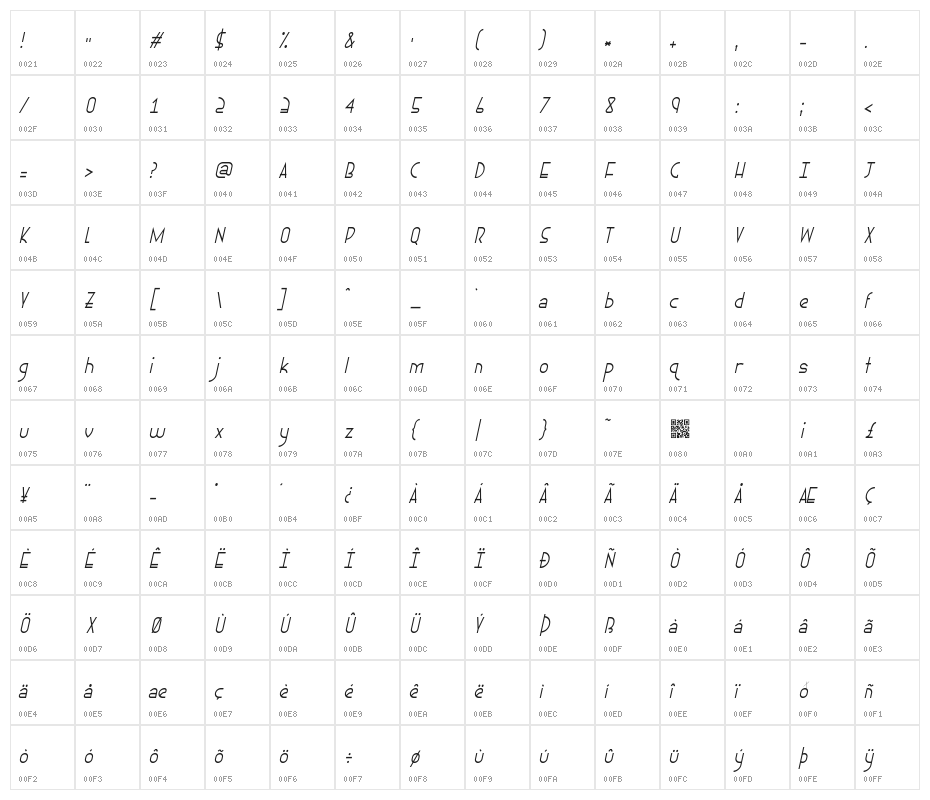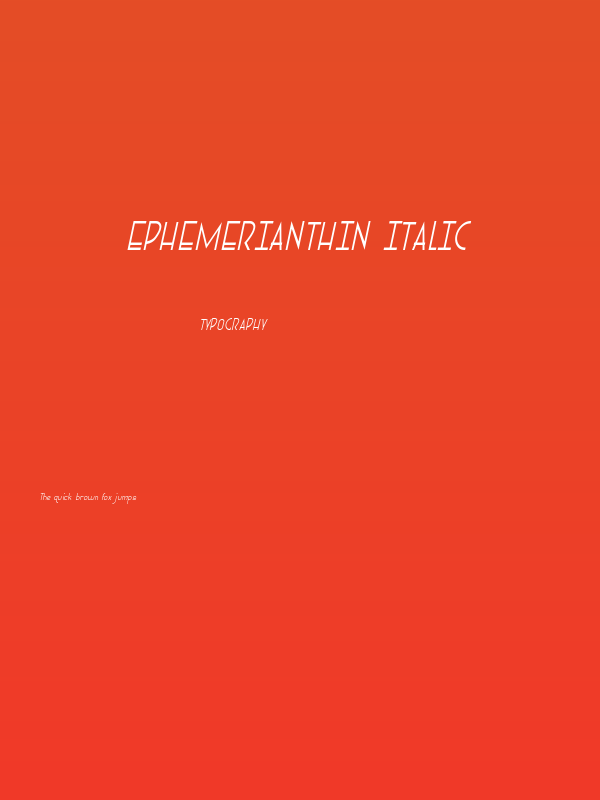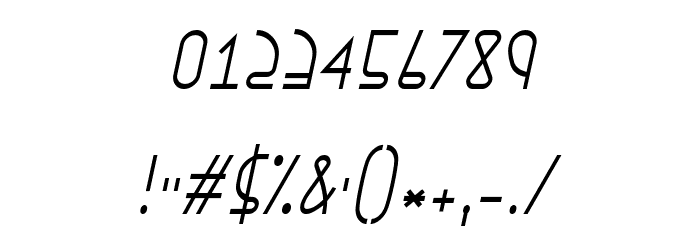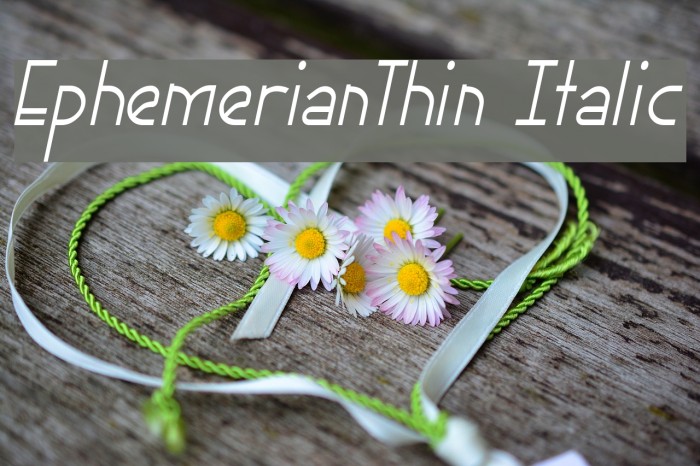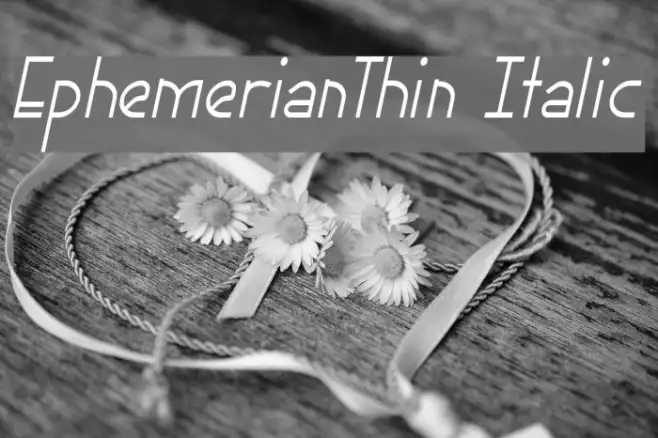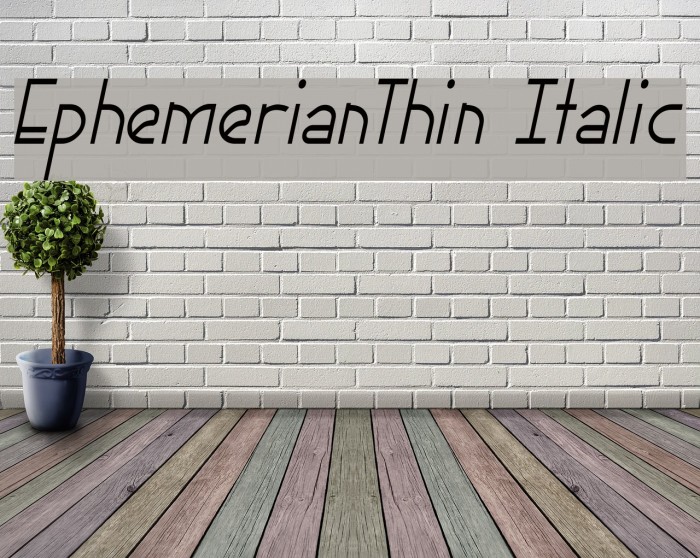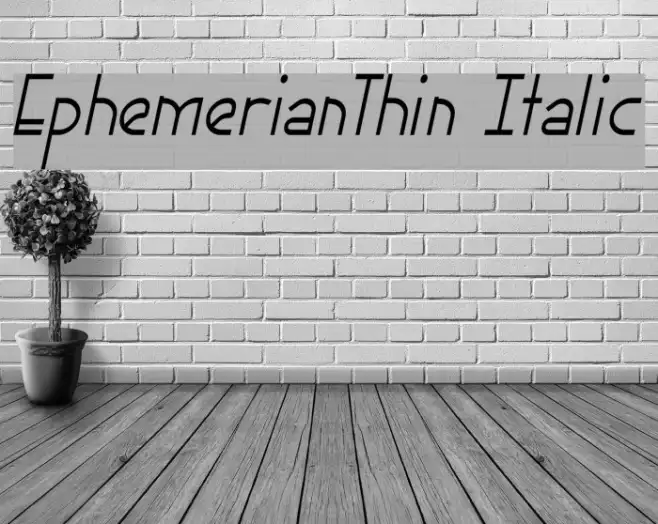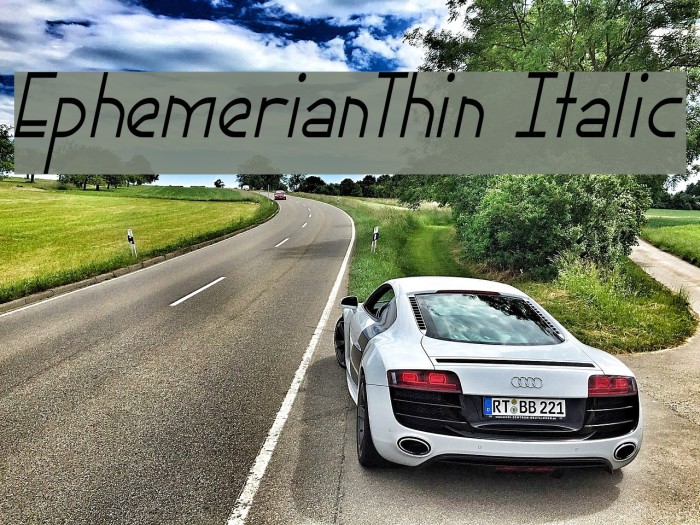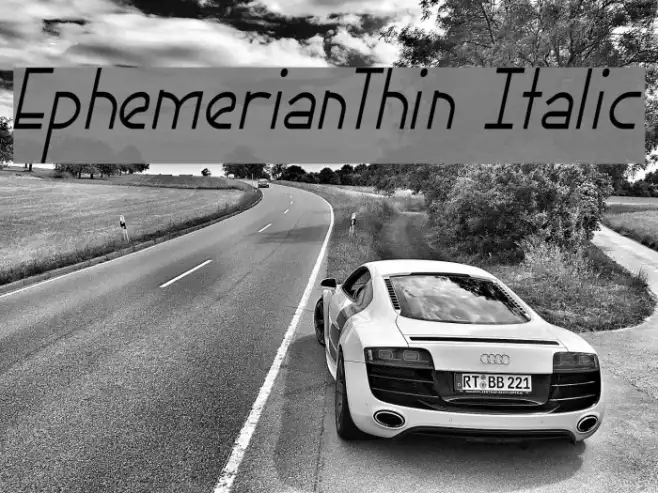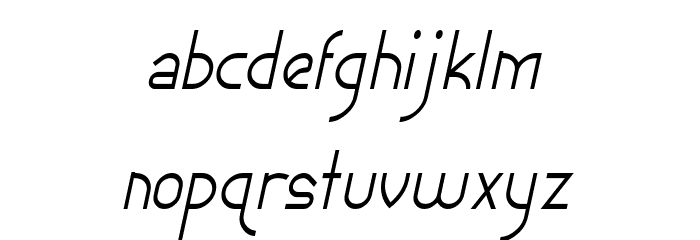
EphemerianThin Italic Font
✎ Retro
| Cas d'utilisation | Headlines, Logos, Invitations |
| Projets proposés | Ideal for fashion magazines, modern branding, elegant invitations, and digital media that require a contemporary and stylish appearance. |